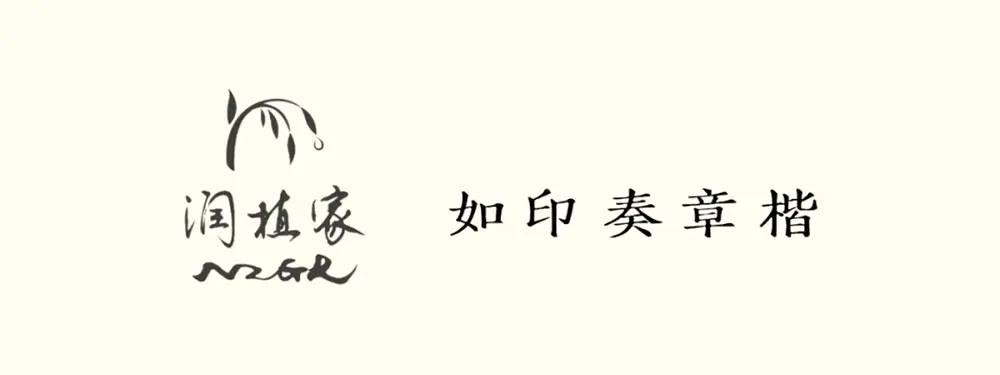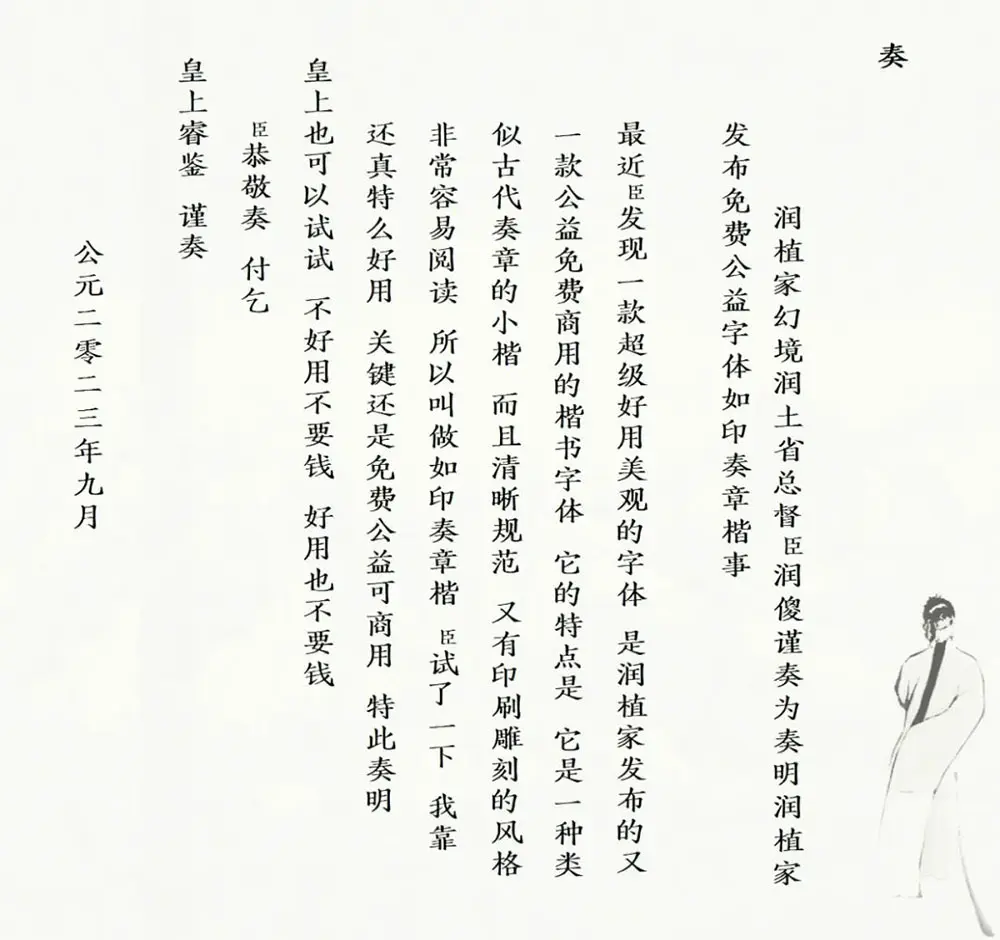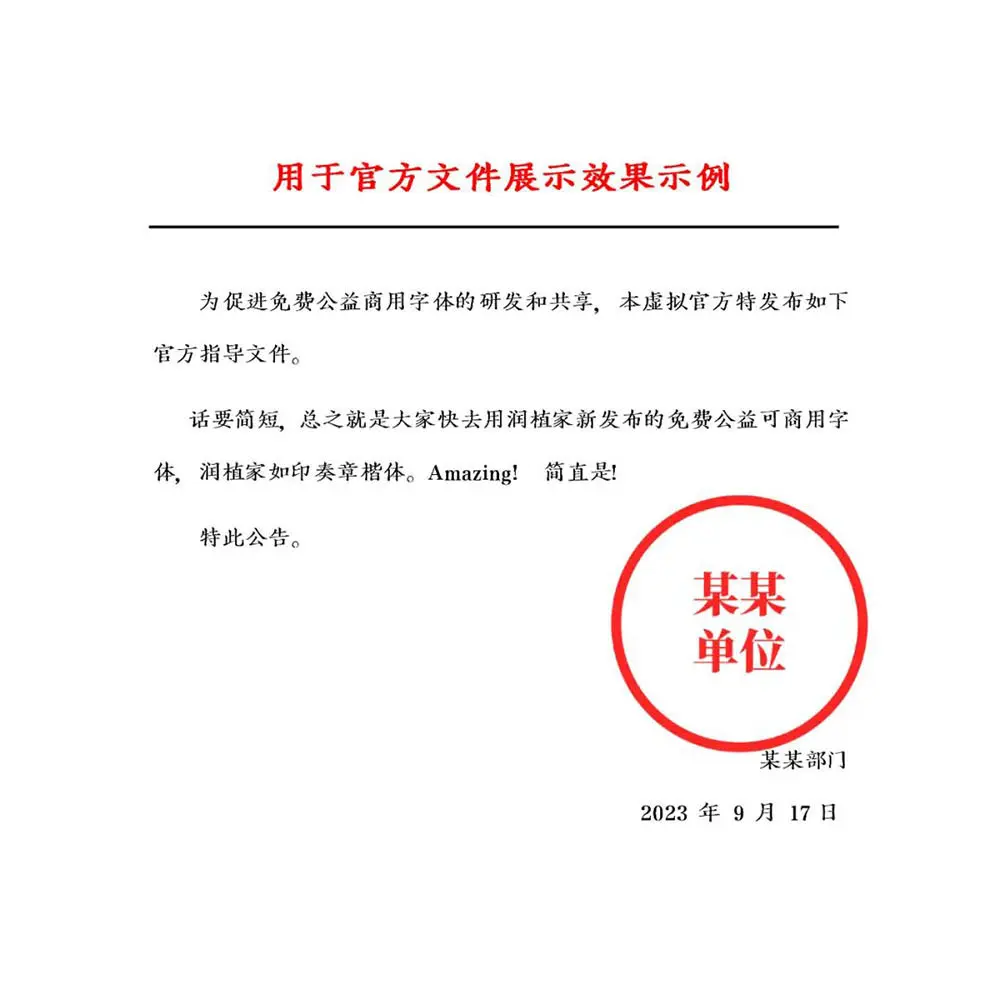
此前,潤植家曾發佈免費商用字體“潤植家康熙字典美化體(常規款和清瘦款)”,免費商用簡體宋體風格字體“潤植家刻本簡體”等,廣受好評。但目前還有沒適用於常規排版閱讀、並且又古籍風格的簡體楷體系列。今天,我們上線一款全新的楷體字體:潤植家如印奏章楷!仍然是關注公眾號,即可免費可商用的使用。
這款字體專用於大量文字,作為正文,豎排和橫屏都好看,並且具有官方正式場合使用的氣場,沒有太大的違和感。
為甚麼叫如印奏章楷呢?因為這種規範中庸、有書卷氣、可識別性高、適合長文閱讀的字體,類似傳統小楷書寫的奏章,如果古代用這種字體寫奏章,皇帝看了也會很舒服。但又非純手寫,有刊印風格,非常工整易讀。
下面是模擬奏章的效果,是不是又平和工整、又養眼適合閱讀?
同時,不光是直排的古代文字,橫排也很好看,適合用於一些官方文件的展示哦,下面是用於官方文件展示的效果示例: